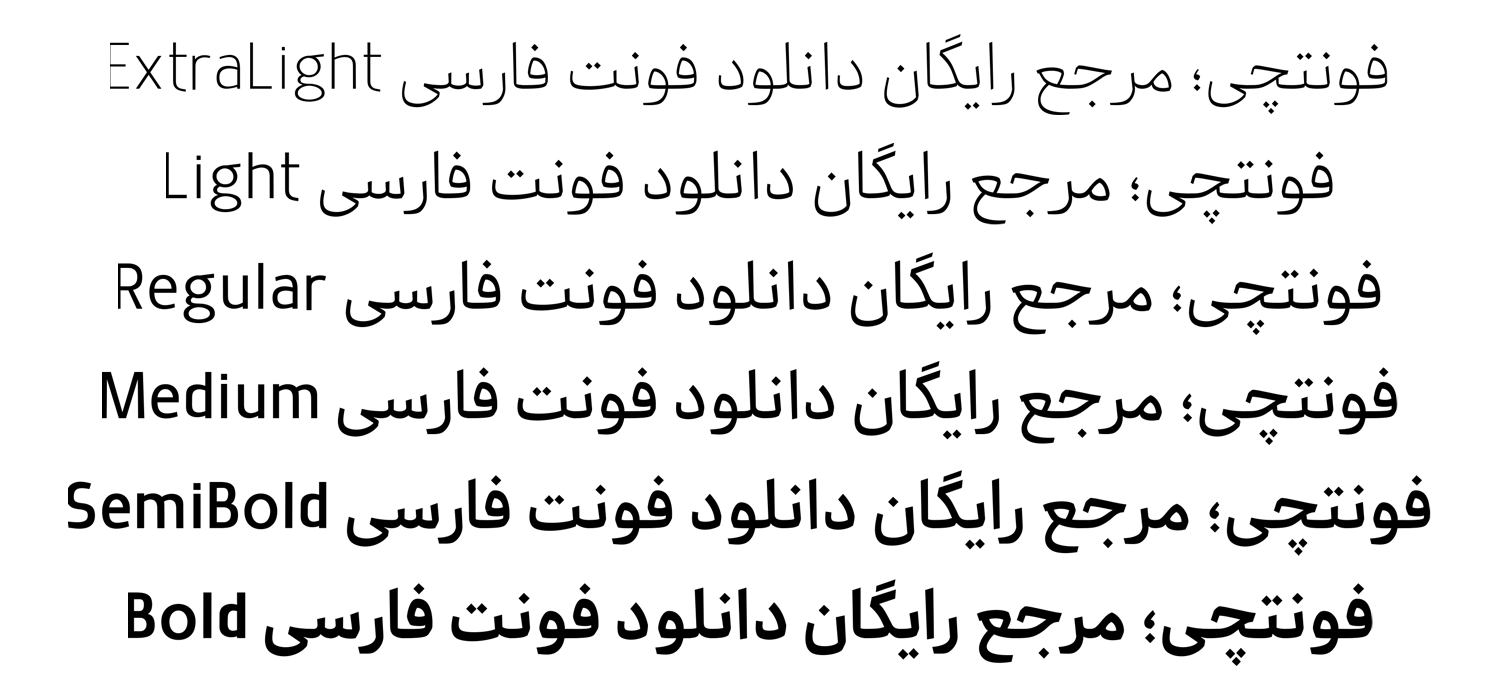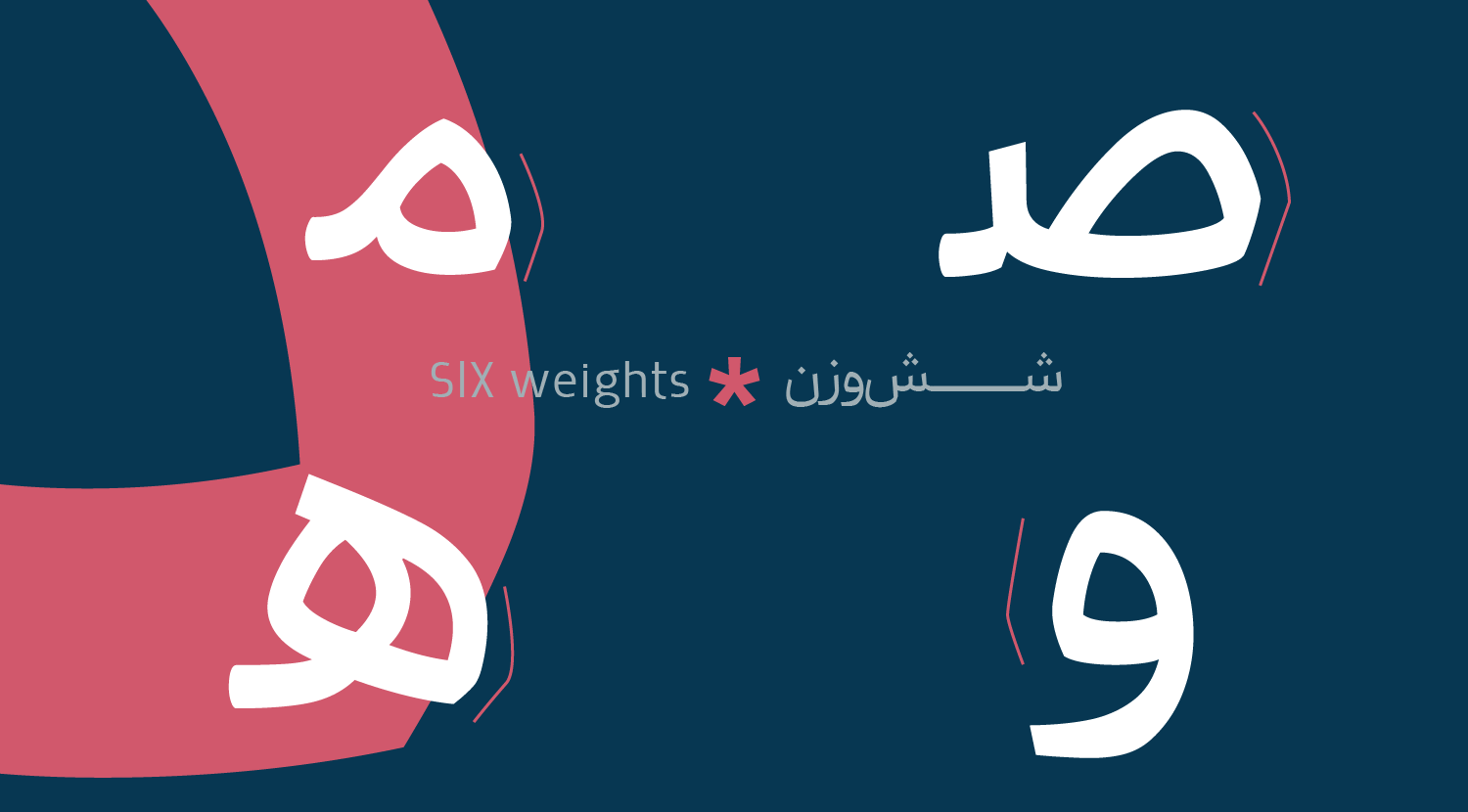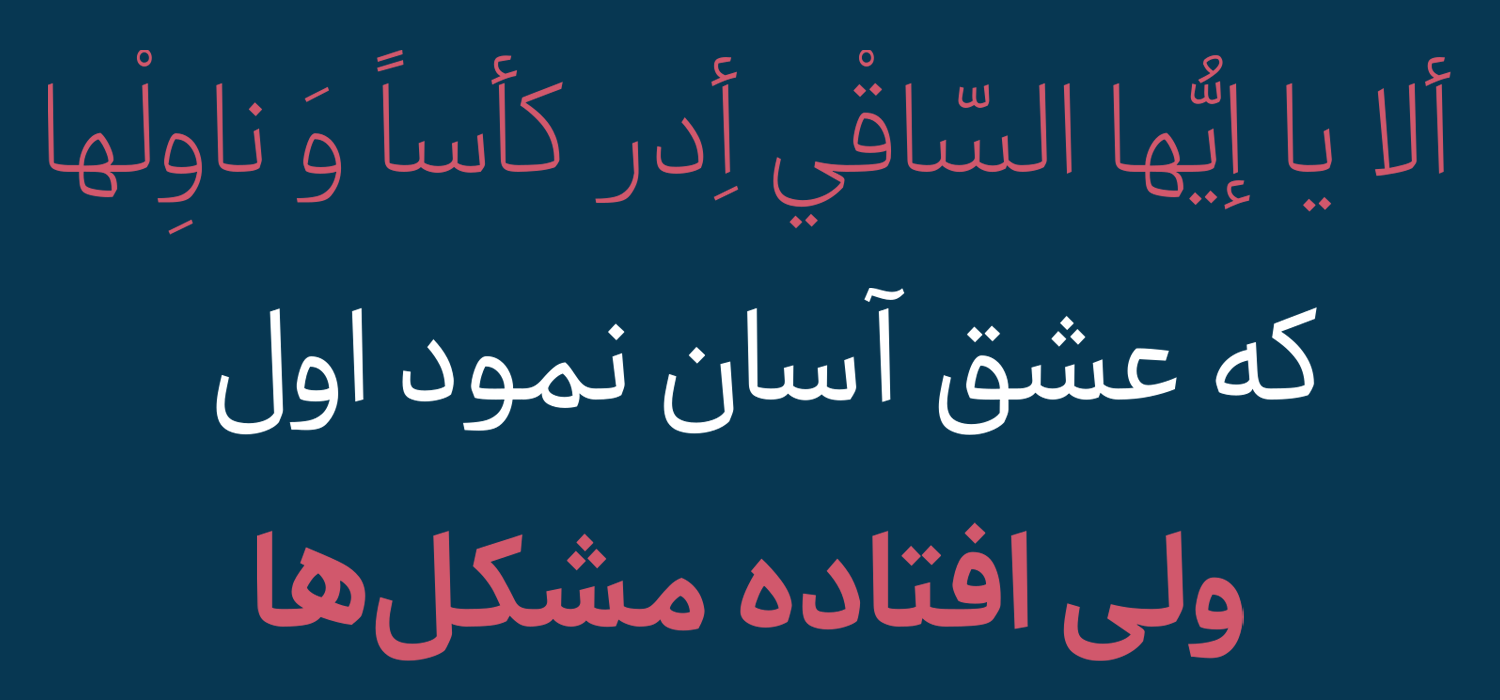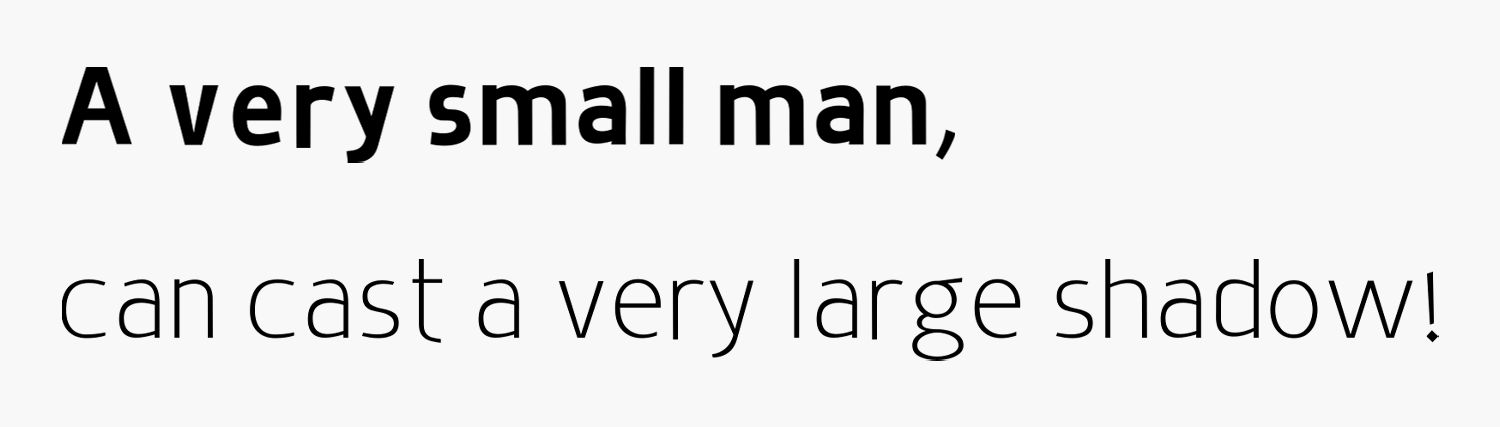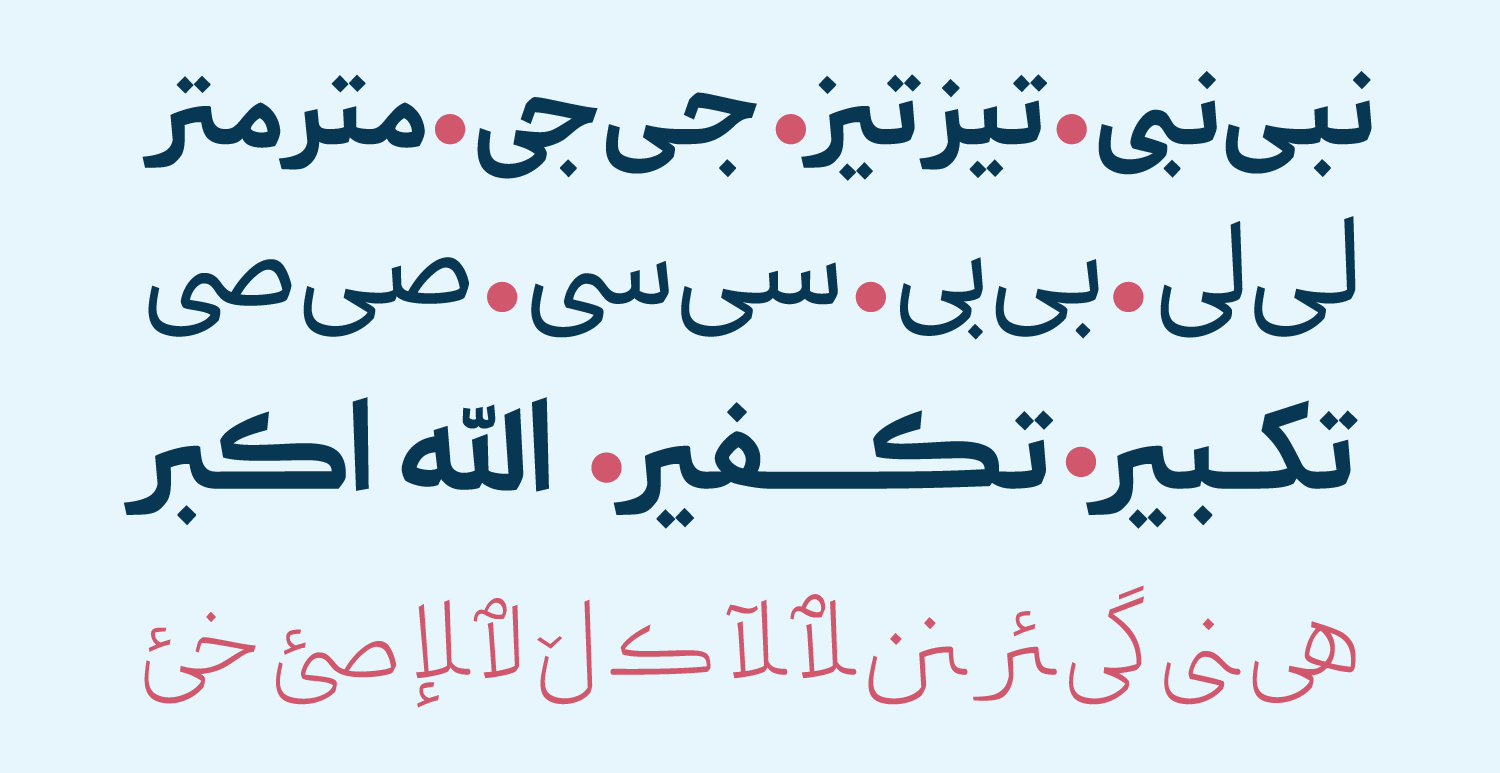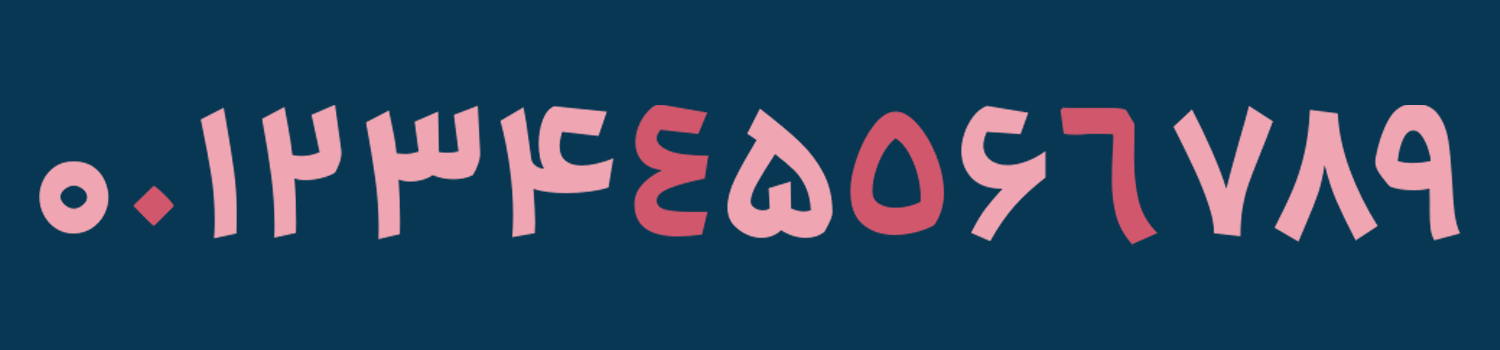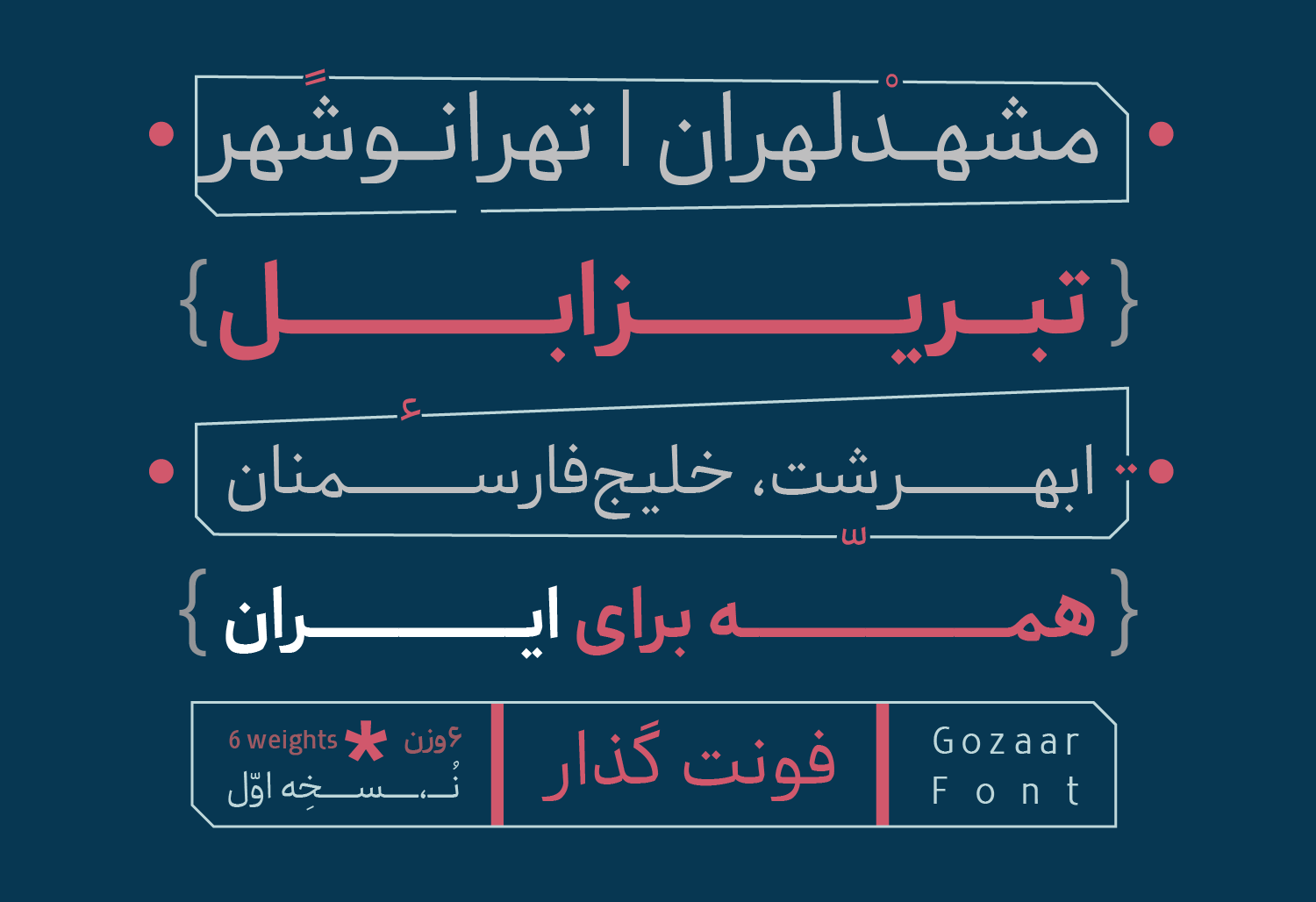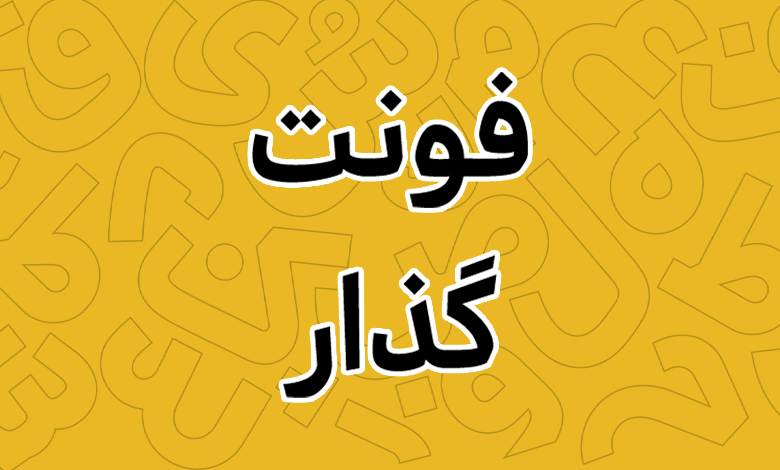
فونت گذار (Gozaar)
فونت گذار (به انگلیسی: Gozaar) با اینکه از سبک نسخ در طراحی پشتیبانی میکند، اما جزو قلمهای مستثنی است که تا حدی هم به فونتهای سنس شباهت دارد. همین ویژگی این فونت تلفیقی را به قلمی تبدیل کرده که میتواند برای استفاده در متون بلند خصوصا در صنعت چاپ گزینهای عالی باشد. فونت گذار رایگان نیست و در دو بسته مختلف و در مجموع با ۶ وزن ارائه شده است.
اگر نیاز به فونتی در صنعت چاپ، کارهای فرهنگی و هنری یا حتی فونت کتب و مجلات دارید، فونت Gozaar میتواند یکی از انتخابهای بهروز و امروزی شما باشد که هر دو سبل نسخ و سنس را در خود دارد. این قلم توسط مهرداد نوتاش طی ۲ سال تلاش طراحی و توسعه داده شده است.
در ادامه این نوشته از سایت فونتچی به نقد و بررسی فونت گذار خواهیم پرداخت. قلمی با ظاهر نسخ قدیمی اما تلفیق شده با خط سنس که سعی شده تمامی بخشهای حروف از چشمیها و منحنیها گرفته تا خطوط عمود و گردیها ضخامت نسبتا یکسانی داشته باشند.
فونت گذار انتخاب مناسبی برای متن کتاب و مطبوعات و همچنین طراحی وبسایت و نرم افزارهایی است که میخواهد حال و هوای اصیل و فرهنگی داشته باشند.
سبک طراحی و وزن فونت گذار
فونت گذار بر پایه خط نسخ طراحی شده است. تمامی حروف مستقل بوده و ظاهر یکپارچه قلم را در تمامی بخشها دارند. اما طراحی آنها طوریاست که وقتی در قالب کلمه و جملات به یکدیگر متصل میشوند، ضخامت کلی بهصورت یکپارچه دیده میشود؛ گویی که این فونت سنس است که با نسخ تلفیق شده است.
در این قلم شاهد ۶ وزن مختلف از خیلی نازک تا بولد هستیم. اینکه خبری از وزنهای بیشتر از بولد همچون سیاه نیست، شاید دلیل خوبی باشد که از این قلم صرفا باید در متون بلند استفاده کنید.
اما با این وجود ظاهر نمایشی این فونت در وزنهای بالاتر خود را بهتر نشان میدهند. خصوصا اینکه در سایز بزرگتری مورد استفاده قرار گیرند. از جمله دیگر قلمهایی که چنین طراحی اما با ظاهر نسخ کامل را دارند میتوان به فونت انجمن اشاره کرد.
پشتیبانی از ۴ زبان متنوع
فونت فارسی گذار جدایی از این زبان، به لطف رسمخط یکسانی که در زبانهای عربی و کوردی شاهدش هستیم از سایر زبانها نیز پشتیبانی میکند. اما انتظار میرود که در نسخههای آتی که فونت ظاهری پختهتر بهخود بگیرد، زبان اردو نیز به این قلم افزوده شود. چرا که این قلم واقعا پتانسیل تبدیل شدن به یک فونت بسیار استاندارد را برای متون بلند دارد.
در نسخه فارسی این قلم تمامی حروف مشترک فارسی و عربی دارای طراحی استاندارد و گلیف اختصاصی خود هستند. این گلیفها متناسب با زبان صفحهکلید تایپ خواهند شد. زمانی که همراه با اعراب باشند، اعراب در موقعیت مناسبی در کنار حروف اصلی قرار میگیرند که از نظر فاصله و چیدمان متن را کاملا یکپارچه نشان خواهد داد.
با اینکه این قلم از زبان لاتین پشتیبانی میکند، اما بهاین صورت نیست که حروف انگلیسی دارای طراحی اختصاصی باشند. بلکه از یک قلم پیشفرض برای حروف لاتین استفاده شده است.
ولی با این همه برای استفاده از کلمات انگلیسی لزومی به تغییر قلم نخواهید داشت.
دارای تنوع در حروف جایگزین فارسی و عربی
حروف جایگزین که به صورت تکی یا همراه با ترکیبات دوتایی هستند امکان تایپ متفاوت کلمات را به شما میدهند. در این قلم همانطور که در تصویر زیر مشاهده میکنید ترکیبات و حروف مختلفی وجود دارد که ظاهری متفاوت برایتان فراهم میکنند.
این نوع حروف جایگزین از دو جهت اهمیت دارد. اول اینکه لزومی به استفاده از کارهای پیچیده گرافیکی برای پیادهسازی این نوع سبک نوشتن با این قلم نخواهید داشت. از سوی دیگر برای زمانی که بخواهید از این قلم در عناوین و با هدف نمایشی (خصوصا در وزن بولد) استفاده کنید، کار شما را سادهتر میکند.
حروف جایگزین موجب جلب توجه خوانندگان خواهد شد و همچنین به زیباتر کردن متن شما نیز کمک میکند. این مدل کاربردها بیشتر در صنعت چاپ و تبلیغات مورد استقبال قرار میگیرند.
پشتیبانی از اعداد فارسی هک شده
قابلیت دیگر فونت گذار پشتیبانی حرفهای از اعداد فارسی و عربی است. در این قلم شاهد پیادهسازی استاندارد اعداد این زبانها هستیم، بهطوریکه با تایپ اعداد در هر یک از این زبانها اعداد به همان شکلی که برای هر زبان است تایپ میشوند.
اعداد عربی «۰۴۵۶» عربی که دارای ظاهری متفاوت به اعداد فارسی «۴۵۶» هستند در این قلم تایپ خواهند شد که در تصویر زیر نمونهای از ظاهر دو زبان را میبینید.
مناسب متون و صنعت چاپ
بهطور کلی فونت گذار برای استفاده در صنعت چاپ بهترین انتخاب خواهد بود. از استفاده برای متون کتب و مجلات گرفته تا چاپ بنرهایی که باحوزه تبلیغات یا بیلبوردهای فرهنگی و هنری باشد.
این قلم با ظاهر نسخ امروزی و دوستانه خود که دارد، ظاهر حروف را در بخش شکستگی حروف دستخوش تغییرات قرار داده است که به خواناتر کردن و نرمتر کردن قلم کمک کرده است.